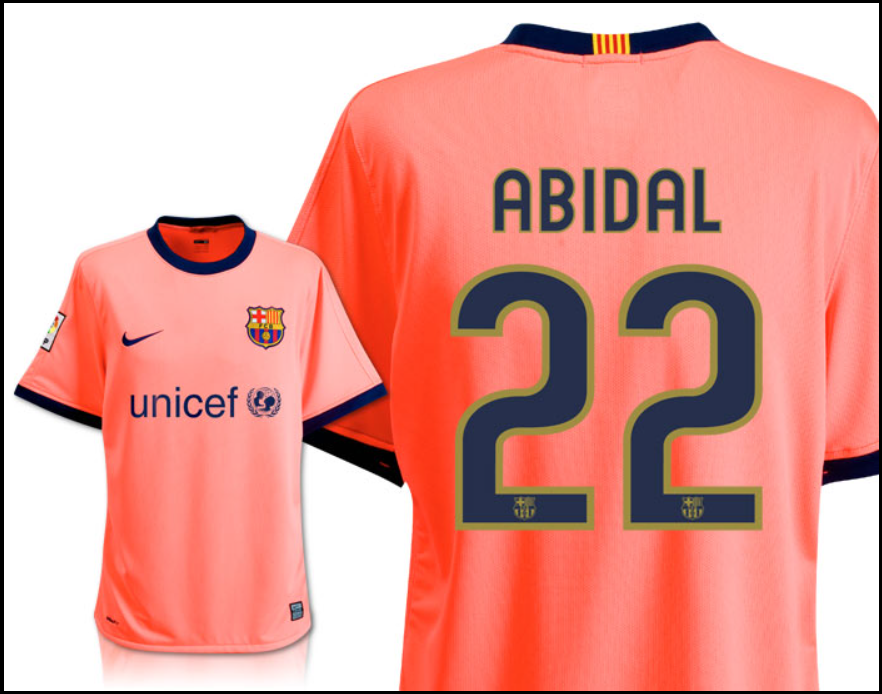
Se existe uma camisa que carrega peso histórico, é a do FC Barcelona da temporada 2008/2009. Foi o início da era Guardiola, o nascimento do “Tiki-Taka” e o ano em que o clube conquistou o histórico Sextete (seis títulos em um ano).
Para designers, colecionadores e apaixonados por camisas retrô, trazemos hoje o arquivo da fonte oficial utilizada pela Nike naquele uniforme icônico “half-and-half” (metade azul, metade grená). Esta é a tipografia que estampou as costas de lendas como Messi (em sua primeira temporada com a 10), Xavi, Iniesta e Eto’o.
Estilo Visual e Identidade
A tipografia desenvolvida pela Nike para a temporada 2009 do Barça foge dos padrões agressivos e pontiagudos comuns nas fontes modernas. Ela apresenta um design mais arredondado e suave (soft sans-serif), transmitindo uma elegância clássica.
Nos uniformes titulares, a fonte era aplicada predominantemente na cor amarela (dourada), criando um contraste perfeito com o azul e grená escuro do kit. A numeração possui uma espessura média, garantindo excelente legibilidade à distância, enquanto os nomes dos jogadores seguem um kerning (espaçamento) ligeiramente mais aberto. É um estilo visual que remete imediatamente ao auge do futebol arte catalão.